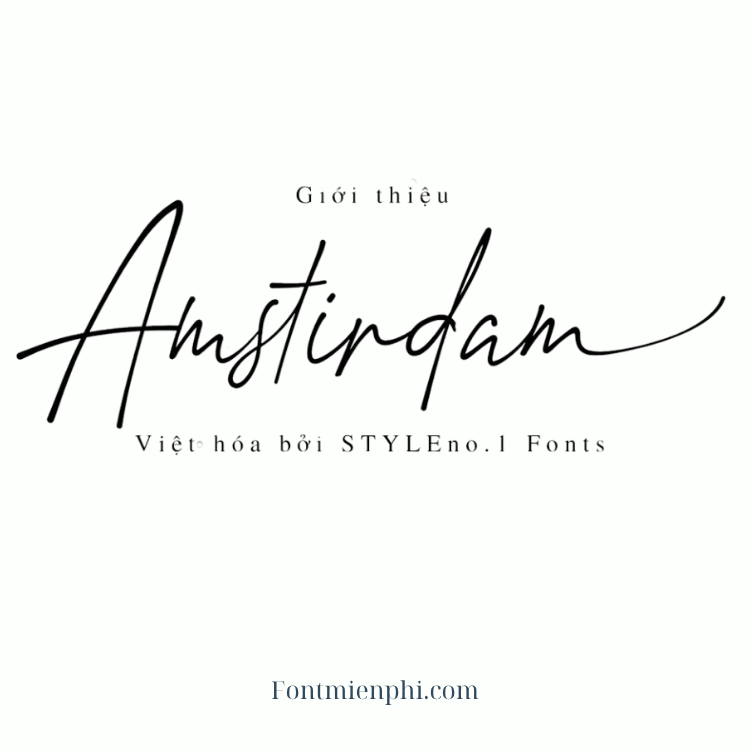
Việt hóa font SVN Amstirdam
Trong thế giới đồ họa hiện đại, việc lựa chọn một Font Chữ phù hợp đóng vai trò quyết định đến tính thẩm mỹ của sản phẩm. Đặc biệt, xu hướng sử dụng Font Miễn Phí ngày càng tăng cao, đòi hỏi các nhà thiết kế phải không ngừng cập nhật những bộ chữ mới lạ. Một trong những cái tên đang làm mưa làm gió hiện nay chính là phiên bản Việt hóa font SVN Amstirdam, một bộ font script mang phong cách viết tay đầy tinh tế và quyến rũ.
Khám phá vẻ đẹp của bộ Việt hóa font SVN Amstirdam
Bộ Việt hóa font SVN Amstirdam nổi bật với những đường nét thanh mảnh, bay bổng nhưng vẫn giữ được sự rõ ràng cần thiết. Đây là lựa chọn hoàn hảo cho các dự án thiết kế thiệp cưới, bìa sách, hoặc các ấn phẩm quảng cáo mỹ phẩm cao cấp. Với bộ mã ký tự đầy đủ, người dùng có thể dễ dàng tạo ra những tác phẩm nghệ thuật mang đậm dấu ấn cá nhân mà không lo lỗi font tiếng Việt.
Ưu điểm vượt trội khi sử dụng font Việt hóa
Phiên bản này đã được tối ưu hóa hoàn toàn về dấu câu, giúp các bạn học sinh và giáo viên dễ dàng ứng dụng vào việc làm slide bài giảng hoặc báo tường. Điểm đặc biệt của font là khả năng kết hợp linh hoạt với các font sans-serif hiện đại, tạo nên sự tương phản thú vị và chuyên nghiệp cho bố cục trang web hay banner mạng xã hội.
Cách ứng dụng Việt hóa font SVN Amstirdam hiệu quả
Để tận dụng tối đa vẻ đẹp của bộ font này, bạn nên sử dụng cho các tiêu đề chính hoặc các đoạn trích dẫn ngắn. Tránh sử dụng cho các văn bản dài vì tính chất uốn lượn có thể gây mỏi mắt cho người đọc. Việc cài đặt cũng rất đơn giản, chỉ cần tải về và sao chép vào thư mục font của hệ thống là bạn đã có thể bắt đầu sáng tạo ngay lập tức.